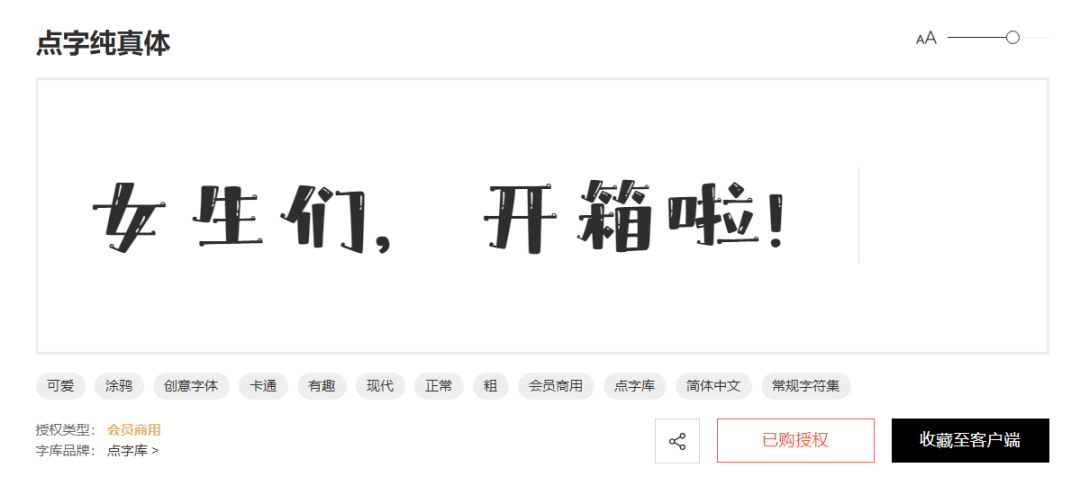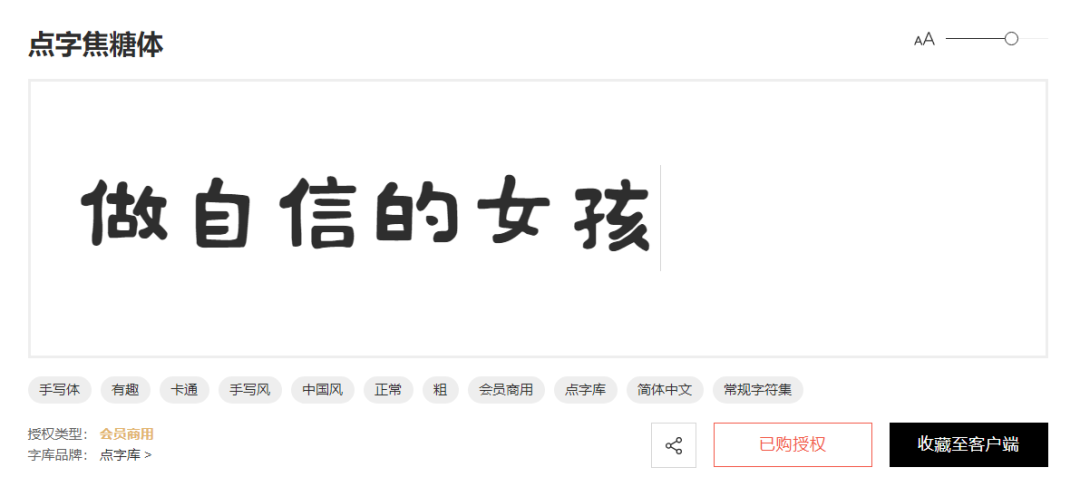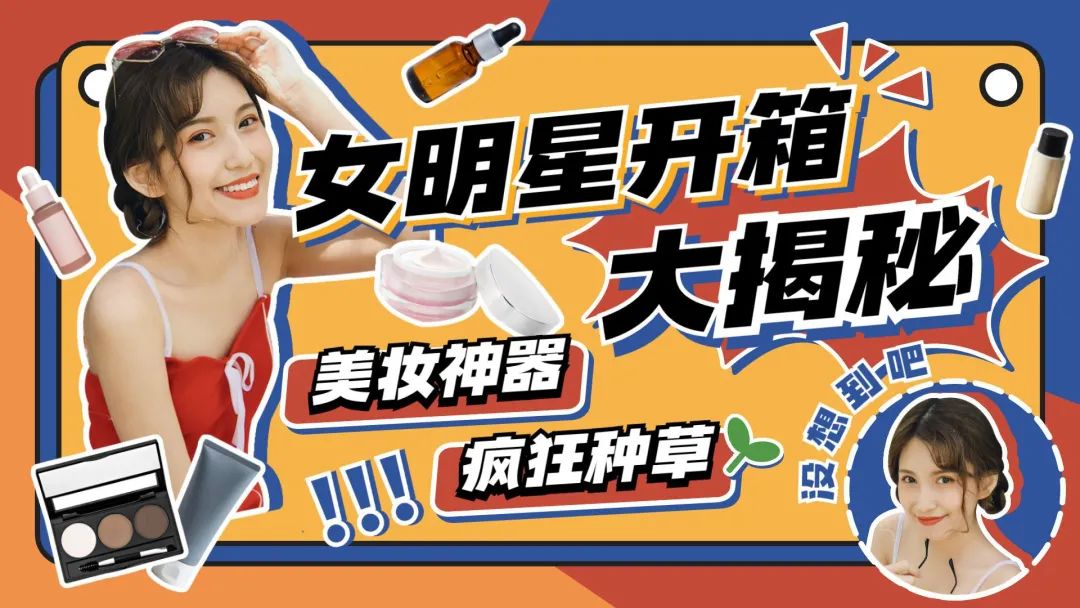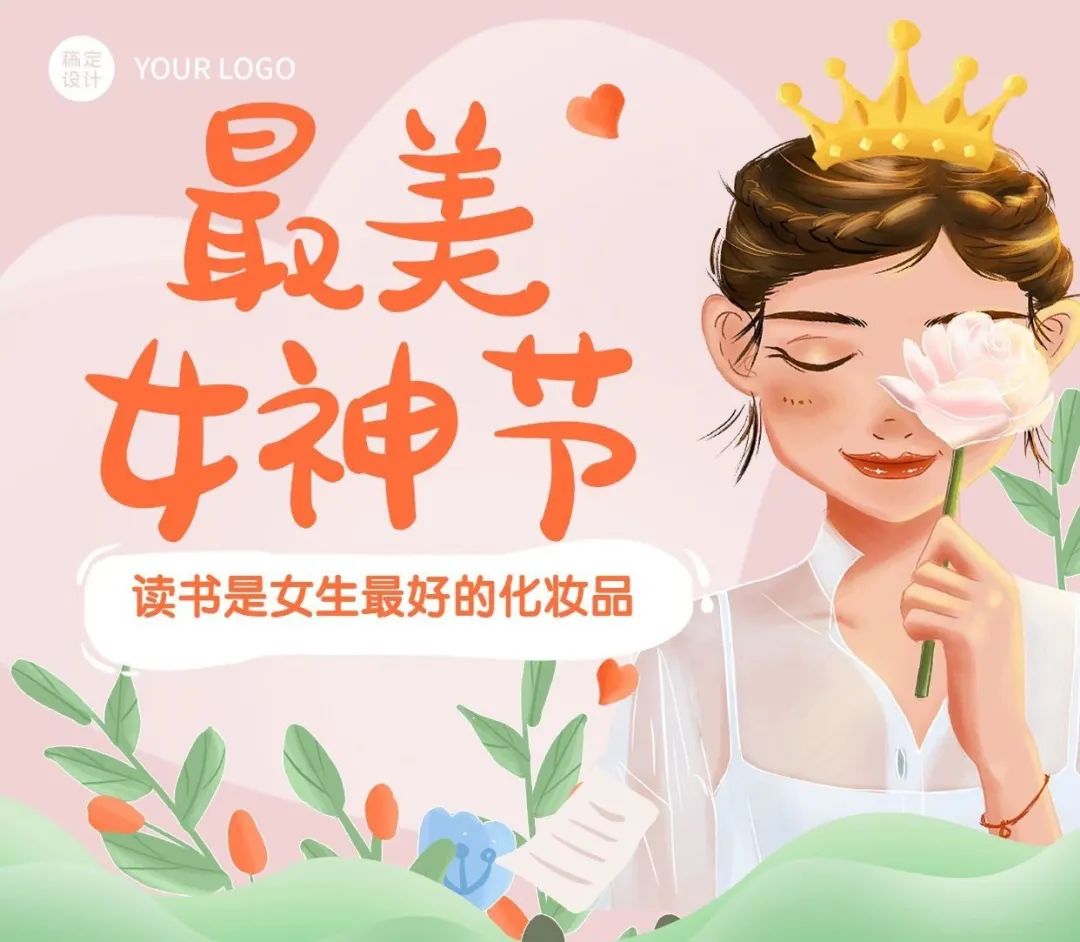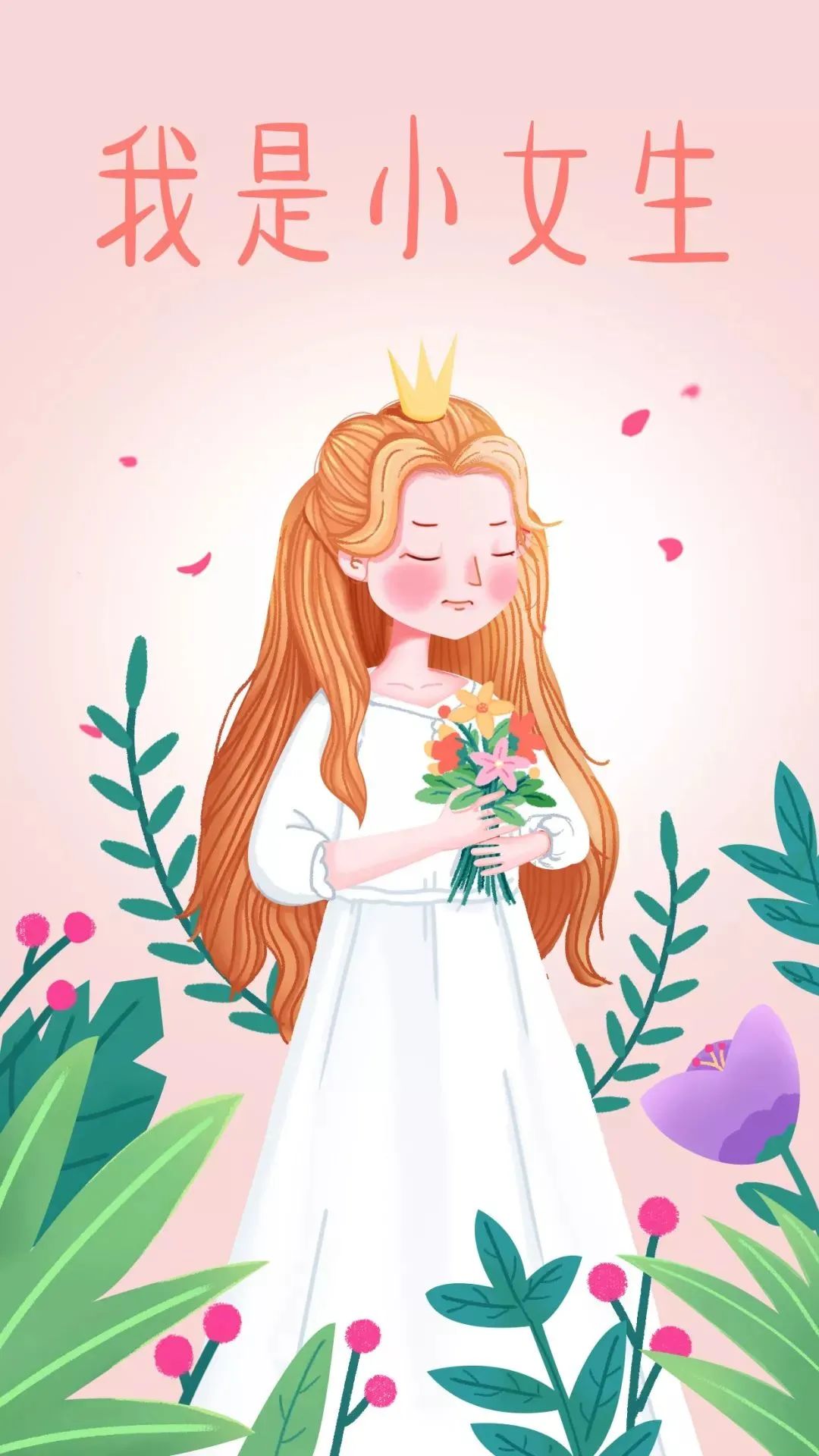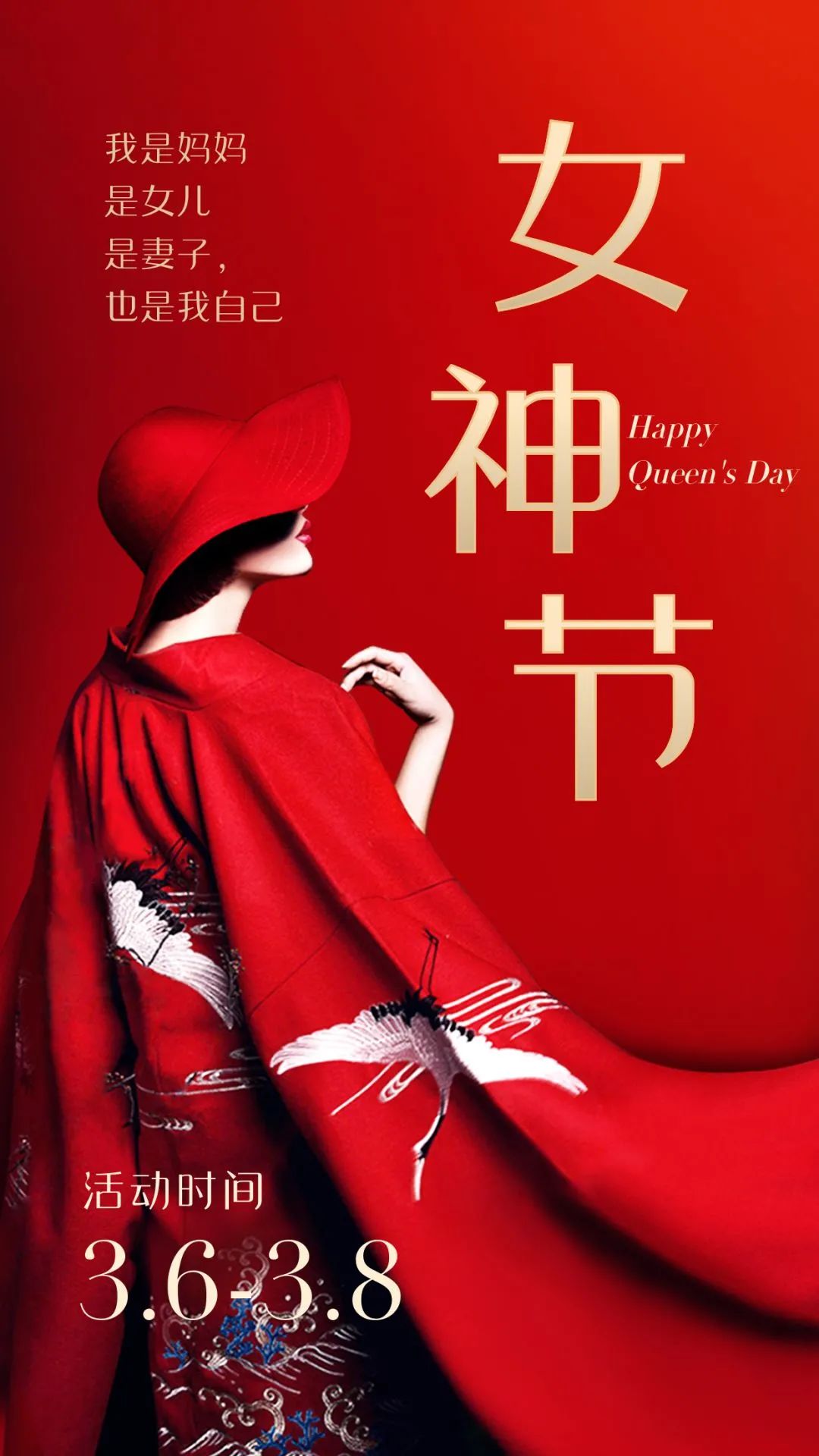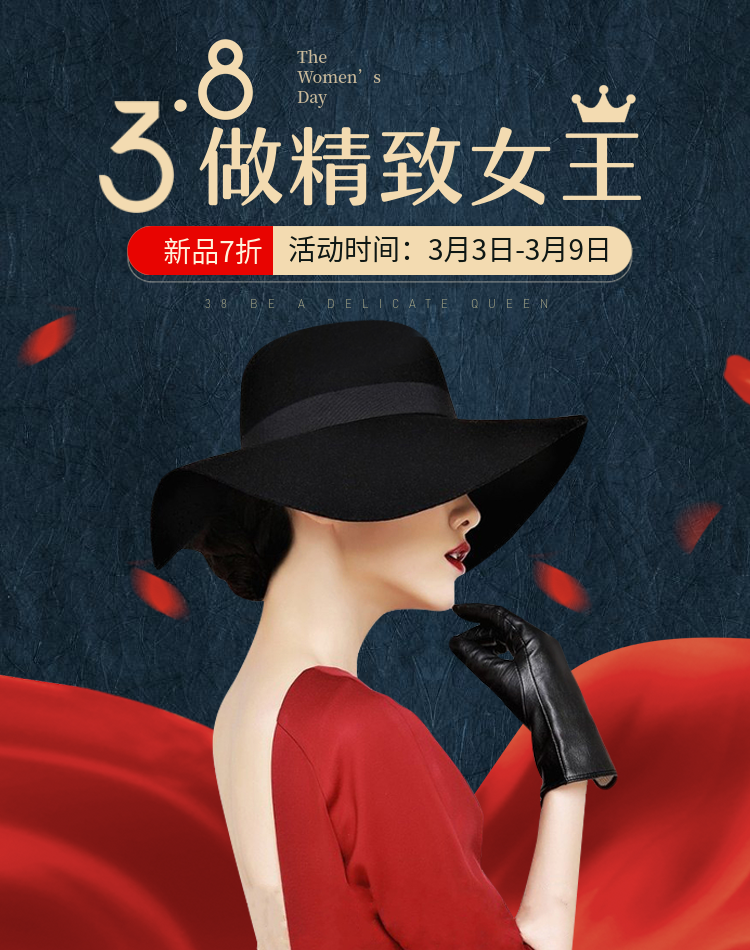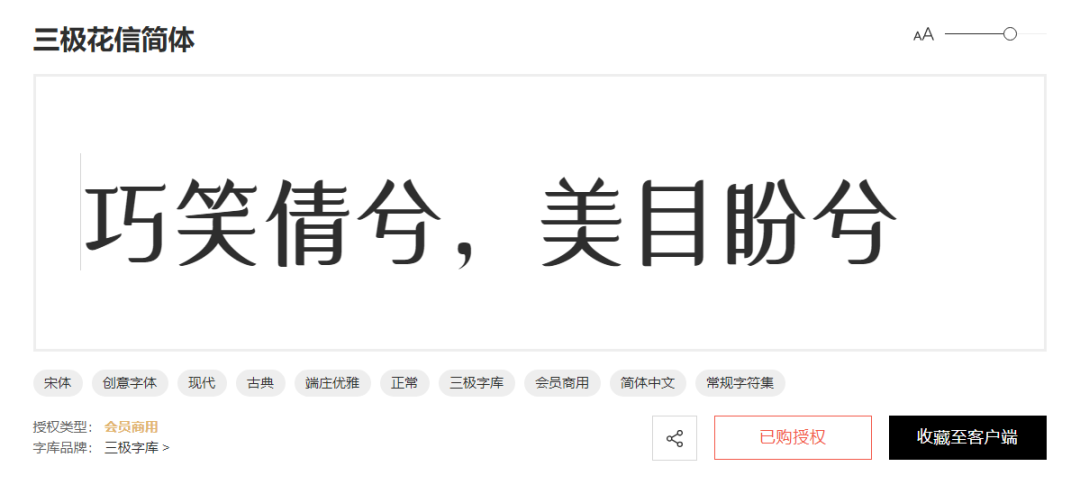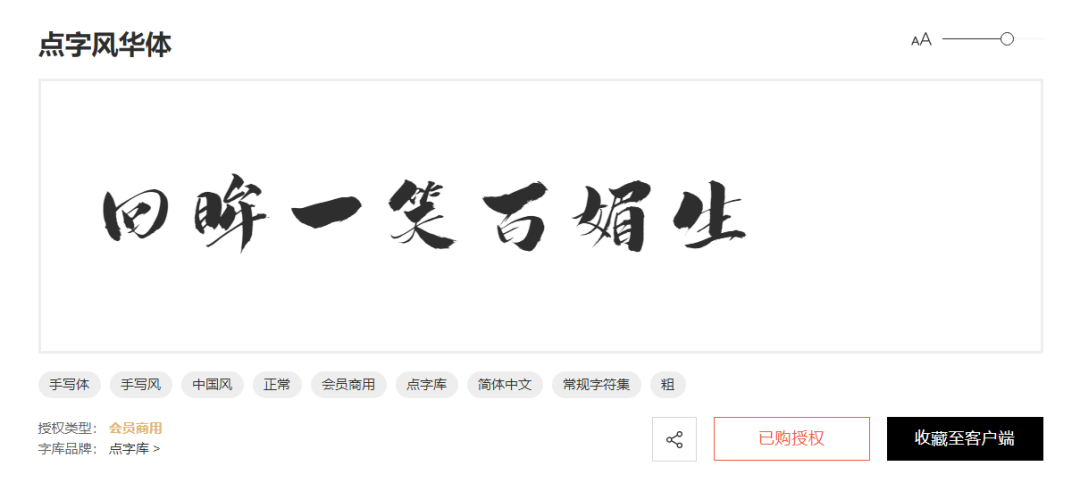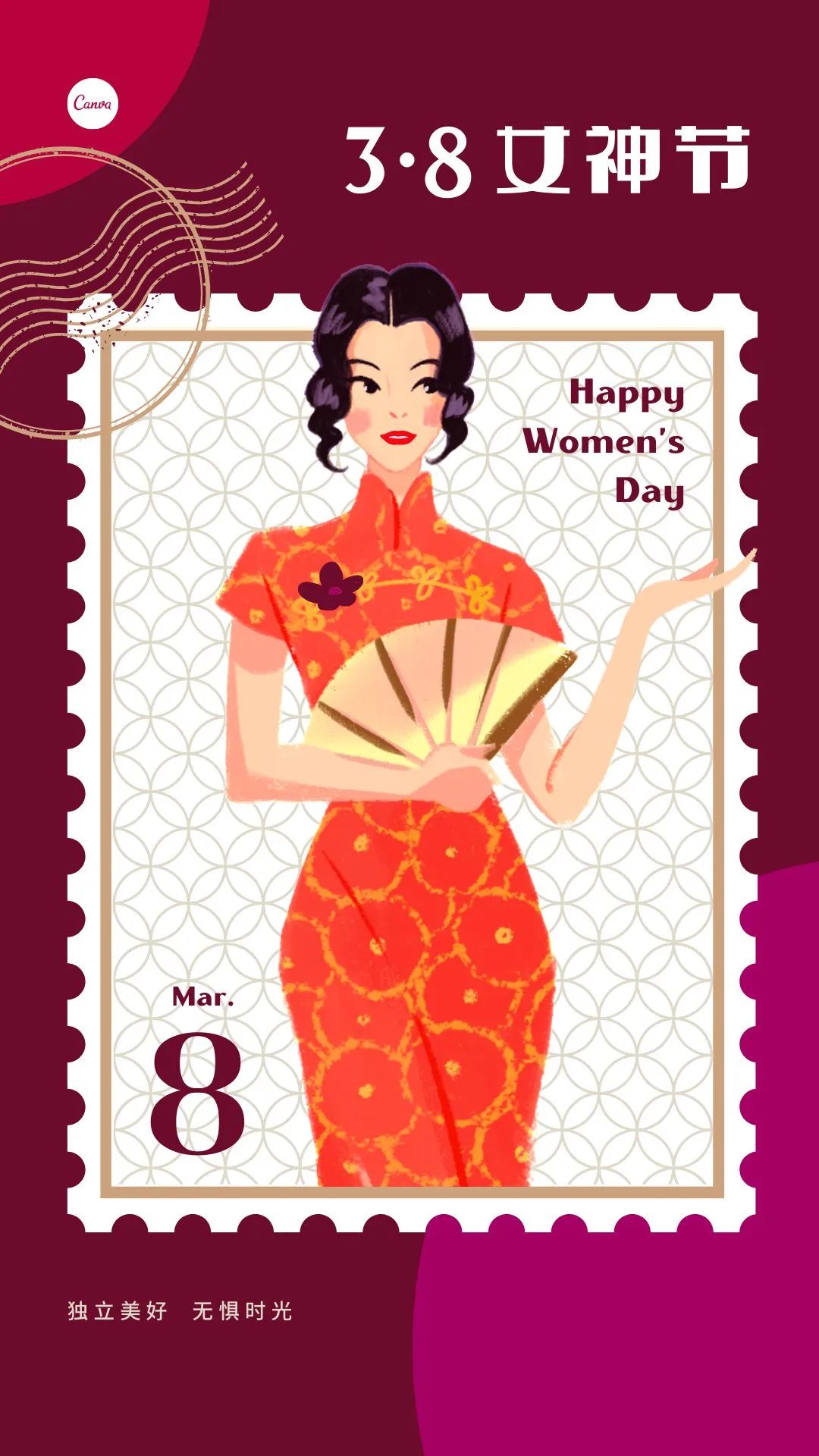
女神节应该用什么字体,一篇文搞定女神节终极选字攻略!
再过几天就是38节了,每年这个时候商家们都会争先恐后地营销,毕竟抓住了女人的心,就算是抓住了钱袋子。
但如何抓住女人的心呢,今天柚子就从字体的角度来说说~
可爱女人
首先不同风格的女性,要用不同的字体来表达,比如走可爱路线的女人,对小清新、软萌圆润的东西,最是没有抵抗力~
▲点字墩墩体(会员商用)
▲胡晓波骚包体(免费商用)
▲汉仪喵魂体(商业需授权)
成熟女王
到了霸气侧漏的女人,表面的“花枝招展”已经吸引不到她,而是一切看起来有质感的东西。
▲汉仪晓波美妍体(商业需授权)
▲汉仪瑞意宋(商业需授权)
▲汉仪润圆(商业需授权)
古典仙女
当国潮文化越来越深入人心,很多女性对东方美、复古风的事物,也是情有独钟。
▲点字美玲体(会员商用)
▲点字大字报(会员商用)
▲字由芳华体(免费商用)
当然这三类还不足以概括所有女性,还有打破一切束缚的自由女人……
▲点字逸致体(会员商用)
还有由你来诠释的新女性形象,字体素材已备好,接下来就看你的了!